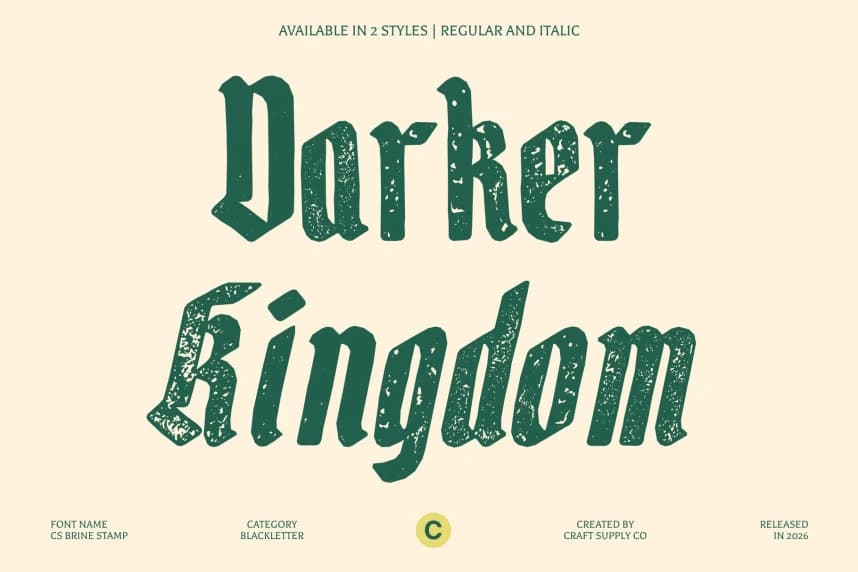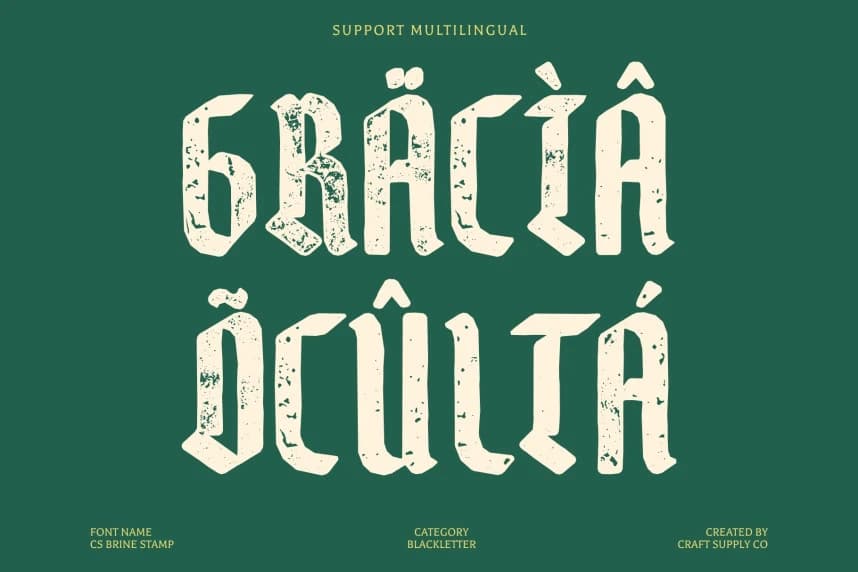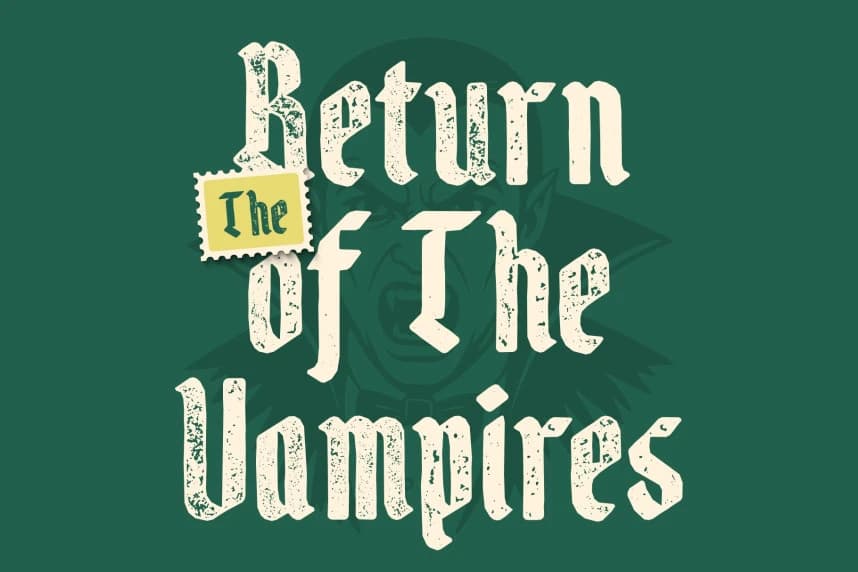
CS Brine Stamp Font – Tarihî dokulu Blackletter Font, özenle tasarlanmış bir Blackletter Gösterim Yazı Tipidir. Bu, zengin detaylı harf biçimleri ve kalın, keskin hatlarıyla büyüleyen çarpıcı bir Blackletter Gösterim Yazı Tipidir.
CS Brine Stamp Font – Blackletter Font Tarihsel Doku ile İnce İşçilikle Tasarlanmış Blackletter Display Font. Bu, zengin ayrıntılı harf biçimleri ve kalın, keskin yapılarla büyüleyen çarpıcı bir blackletter display font.